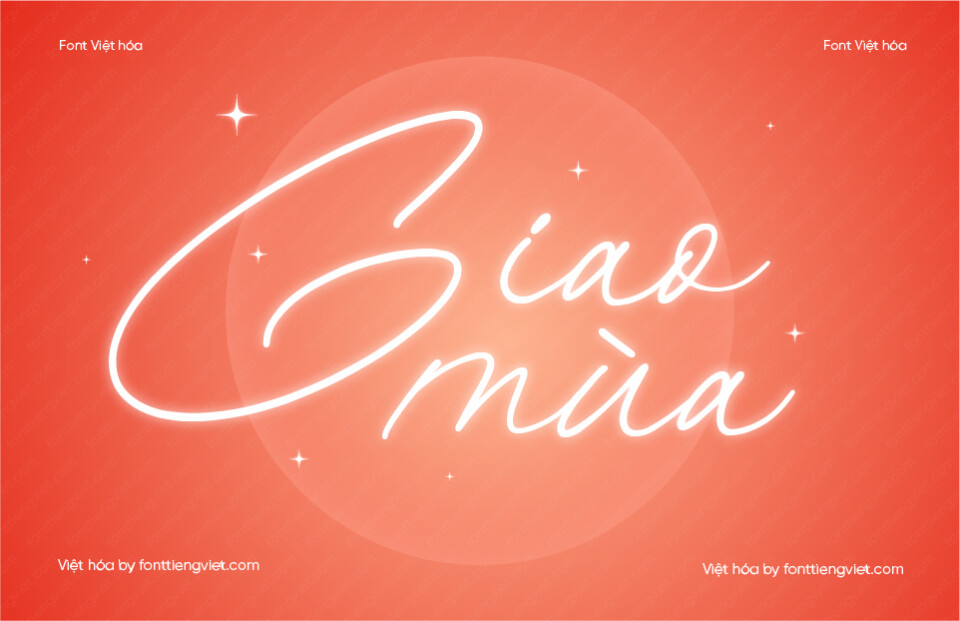
Trong thế giới số hóa ngày nay, việc lựa chọn một Font Chữ phù hợp không chỉ dừng lại ở tính thẩm mỹ mà còn ảnh hưởng trực tiếp đến khả năng truyền tải thông điệp. Đặc biệt với tiếng Việt, một bộ font chất lượng, được Việt hóa cẩn thận là yếu tố then chốt. Và cái tên đang làm mưa làm gió trong cộng đồng thiết kế, học sinh, sinh viên không ai khác chính là Font Việt hóa 1FTV VIP Sontheval. Đây không chỉ là một bộ font thông thường, mà là một công cụ mạnh mẽ giúp nâng tầm mọi dự án, từ bài luận văn học thuật đến các ấn phẩm đồ họa chuyên nghiệp, đảm bảo sự rõ ràng, dễ đọc và tính thẩm mỹ cao. Font này mang đến sự hoàn hảo cho các tác phẩm yêu cầu tính chuyên nghiệp và sự tinh tế trong từng nét chữ, giúp người dùng tự tin hơn với sản phẩm của mình.
Tại Sao Font Việt hóa 1FTV VIP Sontheval Lại Quan Trọng?
Đối với bất kỳ ai làm việc với văn bản tiếng Việt, việc sử dụng font chữ không được Việt hóa đầy đủ có thể dẫn đến nhiều vấn đề như lỗi hiển thị ký tự, khoảng cách chữ không đều, hoặc thậm chí là mất đi vẻ đẹp vốn có của văn bản. Font Việt hóa 1FTV VIP Sontheval ra đời để giải quyết triệt để những vấn đề này. Nó được tối ưu hóa đặc biệt cho tiếng Việt, đảm bảo rằng tất cả các dấu, chữ cái có dấu và ký tự đặc biệt đều hiển thị một cách hoàn hảo, không bị lỗi phông hay xô lệch. Sự chăm chút tỉ mỉ trong từng chi tiết của font này giúp văn bản của bạn không chỉ dễ đọc mà còn toát lên vẻ đẹp tinh tế, chuyên nghiệp, phù hợp với mọi ngữ cảnh sử dụng từ tài liệu học đường đến các ấn phẩm thương mại.
Việc Việt hóa chất lượng cao còn mang lại lợi ích lớn trong việc duy trì tính nhất quán và đồng bộ cho các tài liệu. Khi bạn cần in ấn tài liệu, sự ổn định của font chữ là cực kỳ quan trọng. Font Việt hóa 1FTV VIP Sontheval giúp loại bỏ nỗi lo về việc font bị thay đổi khi chuyển từ màn hình sang giấy, hay từ máy tính này sang máy tính khác. Đây là một yếu tố không thể thiếu đối với các bài thi tốt nghiệp, đồ án cuối kỳ hay các báo cáo khoa học, nơi mà sự chính xác và rõ ràng là tối thượng. Font này được nhiều người dùng đánh giá cao về độ tương thích và khả năng hiển thị trên nhiều nền tảng khác nhau, từ đó mang lại trải nghiệm tốt nhất cho người dùng.
Ứng Dụng Đa Dạng Của Font 1FTV VIP Sontheval Trong Học Tập và Công Việc
Đối Với Học Sinh và Sinh Viên
Học sinh và sinh viên thường xuyên phải đối mặt với việc soạn thảo tài liệu, bài tập, thuyết trình, và đặc biệt là các bài luận văn, đồ án tốt nghiệp. Một bộ font chữ đẹp, chuyên nghiệp như Font Việt hóa 1FTV VIP Sontheval có thể tạo ra sự khác biệt lớn. Nó giúp bài viết của bạn trông gọn gàng, dễ đọc hơn, từ đó gây ấn tượng tốt với giáo viên và người chấm. Thay vì phải lo lắng về việc font bị lỗi, các bạn có thể tập trung hoàn toàn vào nội dung. Font này cũng rất phù hợp cho việc thiết kế bìa tiểu luận, poster dự án hoặc các ấn phẩm truyền thông cho các hoạt động ngoại khóa của trường.
Hỗ Trợ Giáo Viên và Giảng Viên
Giáo viên và giảng viên là những người thường xuyên tạo ra các tài liệu giảng dạy, đề thi, giáo trình và bài giảng. Việc sử dụng Font Việt hóa 1FTV VIP Sontheval giúp đảm bảo tính chuyên nghiệp và rõ ràng cho các tài liệu này. Đề thi có font chữ dễ đọc sẽ giúp học sinh tập trung hơn vào nội dung câu hỏi, tránh nhầm lẫn do lỗi hiển thị. Các bài giảng được trình bày với font đẹp cũng sẽ thu hút sự chú ý của sinh viên hơn, làm cho quá trình học tập trở nên thú vị và hiệu quả hơn. Đây là một công cụ đắc lực giúp nâng cao chất lượng giáo dục và tối ưu hóa quá trình truyền đạt kiến thức.
Nâng Tầm Thiết Kế Đồ Họa và In Ấn
Trong lĩnh vực thiết kế đồ họa và in ấn, font chữ là linh hồn của tác phẩm. Font Việt hóa 1FTV VIP Sontheval với vẻ đẹp hiện đại và khả năng Việt hóa hoàn chỉnh là lựa chọn lý tưởng cho các nhà thiết kế. Từ việc tạo logo, bộ nhận diện thương hiệu, thiết kế bao bì sản phẩm, đến các ấn phẩm quảng cáo, tạp chí hay sách báo, font này đều có thể đáp ứng một cách xuất sắc. Sự sắc nét, tinh tế và tính ổn định của font giúp các sản phẩm in ấn đạt chất lượng cao nhất, thu hút ánh nhìn và truyền tải thông điệp một cách mạnh mẽ, góp phần tạo nên những tác phẩm nghệ thuật đồ họa độc đáo và ấn tượng.
Đặc Điểm Nổi Bật Của Font Việt hóa 1FTV VIP Sontheval
Điều làm nên sự khác biệt của Font Việt hóa 1FTV VIP Sontheval chính là sự kết hợp hài hòa giữa tính thẩm mỹ cao và độ tương thích vượt trội. Font được thiết kế với các nét chữ thanh lịch, hiện đại, phù hợp với nhiều phong cách thiết kế khác nhau. Đặc biệt, quá trình Việt hóa được thực hiện rất kỹ lưỡng, đảm bảo rằng tất cả các ký tự tiếng Việt, dấu thanh đều hiển thị chuẩn xác, không bị biến dạng hay lỗi phông. Khoảng cách giữa các chữ cái (kerning) cũng được tối ưu hóa để tạo ra một dòng chữ liền mạch, dễ đọc và hài hòa. Đây là một yếu tố quan trọng mà nhiều font miễn phí khác thường bỏ qua, dẫn đến việc văn bản trông rời rạc và thiếu chuyên nghiệp. Font còn có nhiều biến thể về độ đậm nhạt, giúp người dùng linh hoạt hơn trong việc lựa chọn và kết hợp các phong cách.
Ngoài ra, Font Việt hóa 1FTV VIP Sontheval còn được biết đến với tính ổn định cao trên nhiều hệ điều hành và phần mềm khác nhau, từ Microsoft Word, PowerPoint, Excel đến các phần mềm đồ họa chuyên nghiệp như Adobe Photoshop, Illustrator, InDesign. Điều này giúp người dùng không phải lo lắng về việc font bị lỗi hoặc không hiển thị đúng khi chuyển đổi giữa các môi trường làm việc. Sự linh hoạt và độ tin cậy này biến Font Việt hóa 1FTV VIP Sontheval thành một tài sản quý giá cho bất kỳ ai muốn nâng cao chất lượng công việc và học tập của mình, đặc biệt là trong các dự án đòi hỏi sự chính xác và đồng bộ cao.
Cách Sử Dụng và Tận Dụng Hiệu Quả Font Này
Một mẹo nhỏ để tận dụng tối đa Font Việt hóa 1FTV VIP Sontheval là kết hợp nó với các font chữ khác một cách hợp lý. Chẳng hạn, bạn có thể sử dụng font này cho tiêu đề và một font khác đơn giản hơn cho nội dung chính để tạo sự tương phản và phân cấp thông tin rõ ràng. Điều này không chỉ làm cho thiết kế của bạn trở nên chuyên nghiệp hơn mà còn giúp người đọc dễ dàng tiếp nhận thông tin hơn. Luôn nhớ rằng mục tiêu cuối cùng là tạo ra một sản phẩm đẹp, dễ đọc và hiệu quả trong việc truyền tải thông điệp, và Font Việt hóa 1FTV VIP Sontheval chắc chắn sẽ là một trợ thủ đắc lực trong hành trình đó.
Tóm lại, Font Việt hóa 1FTV VIP Sontheval không chỉ là một lựa chọn tuyệt vời cho các nhà thiết kế chuyên nghiệp mà còn là một công cụ không thể thiếu cho học sinh, sinh viên và giáo viên trong quá trình học tập và làm việc. Với khả năng Việt hóa hoàn hảo, tính thẩm mỹ cao và độ tương thích rộng rãi, bộ font này chắc chắn sẽ nâng tầm mọi dự án của bạn, từ những bài tập đơn giản đến các đồ án phức tạp. Đừng ngần ngại trải nghiệm sự khác biệt mà bộ Font Chữ này mang lại. Nó sẽ giúp bạn tạo ra những ấn phẩm chất lượng cao, gây ấn tượng mạnh mẽ và truyền tải thông điệp một cách rõ ràng, hiệu quả nhất.